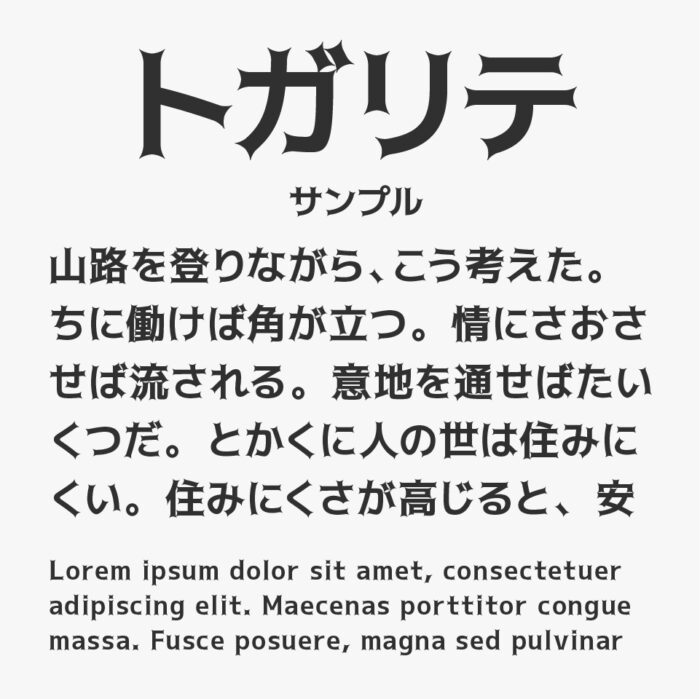
トガリテフォントは、文字の先端にトゲトゲの装飾が施されているフォントになっています。
フォント名の由来は「フランス語で平等を意味する“égalité(リガリテ)”と“尖る”という言葉から“トガリテ(togalité)”と名づけたフォント。」とのことです。
トゲトゲしたフォルムはインパクトがあるので、タイトルやロゴ、動画テロップなどに使ってみると面白いかもしれませんね!ウェイトも7種類用意されているので、シーンにあわせた太さを選べるところも嬉しいポイントです。
収録文字は、ひらかな・カタカナ・半角英数字・記号・漢字:JIS第一水準(2965字)JIS第二水準(2257字)、他が収録されているとのことです。